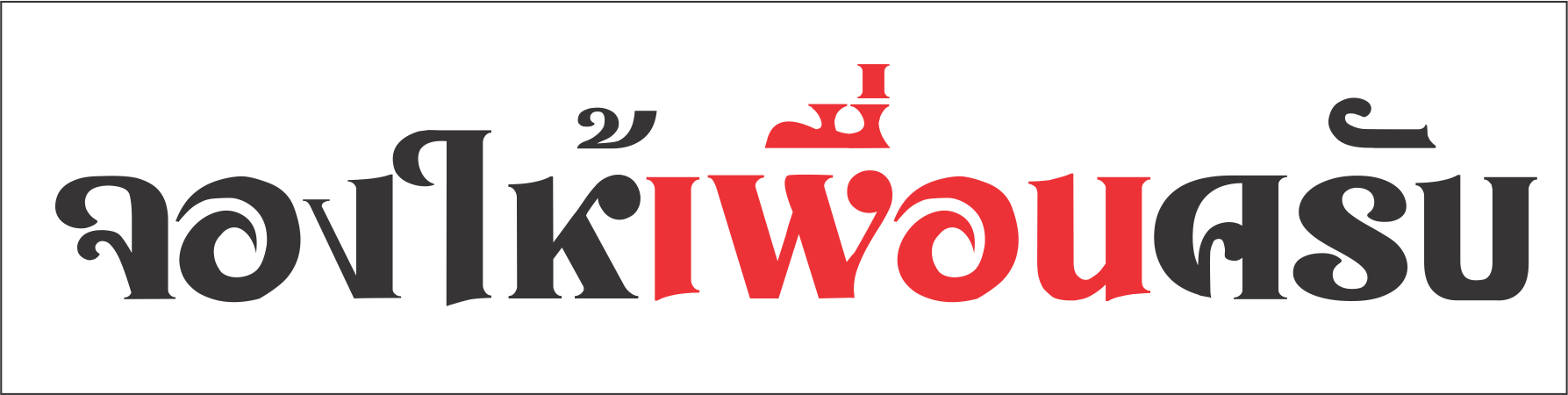
[แตกหน่อ] ฟอนต์ที่หลุดคิวจอง
เป็นอีกหนึ่งฟอนต์สวยๆจากทางค่ายของเรา ใช้งานได้หลากหลายรูปแบบ แนวคิดผสมผสานระหว่างลูกทุ่งกับตัวบรรจง เริ่มต้นด้วยการร่างดินสอลงกระดาษแล้วจับใส่คอมอีกที